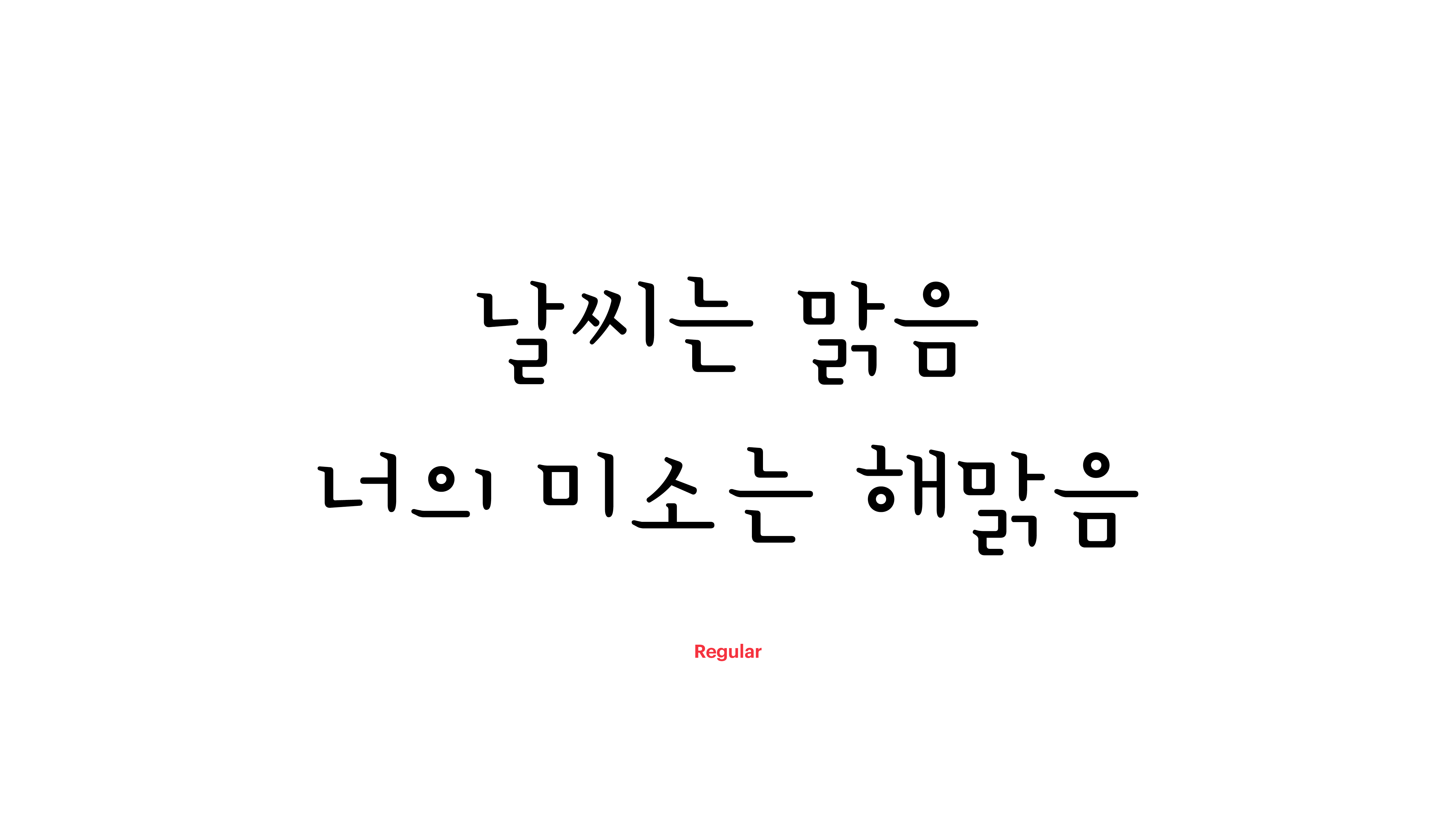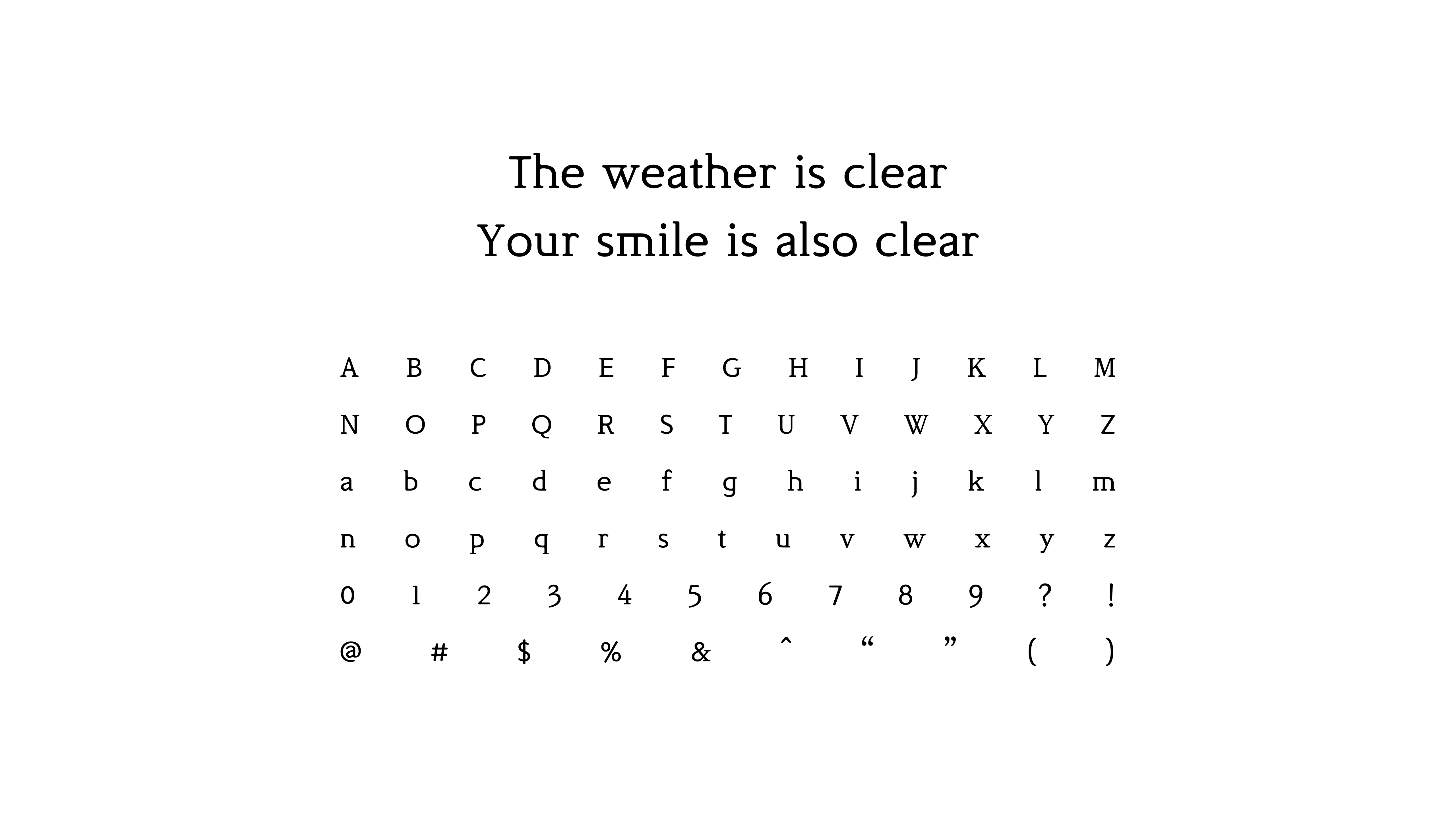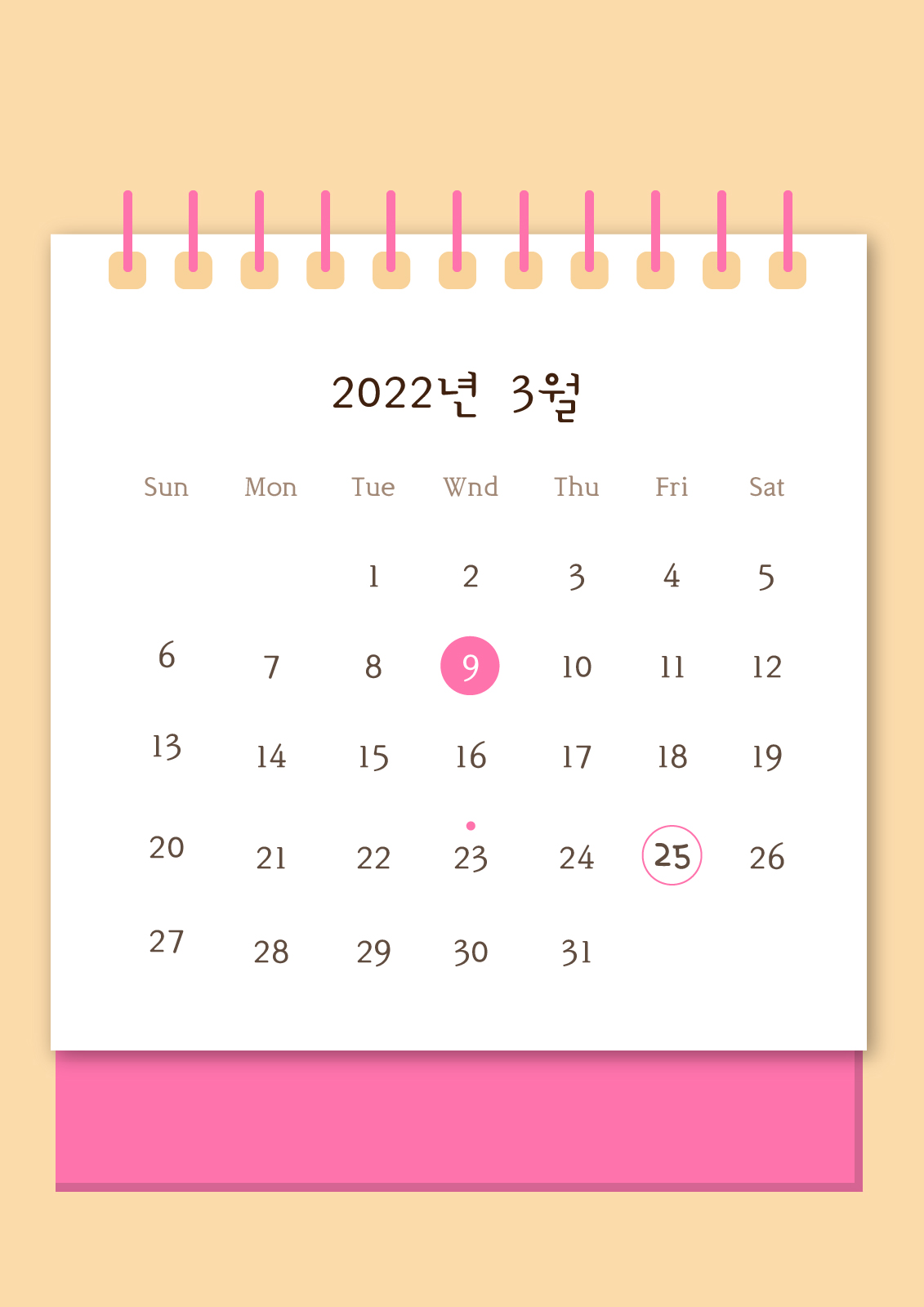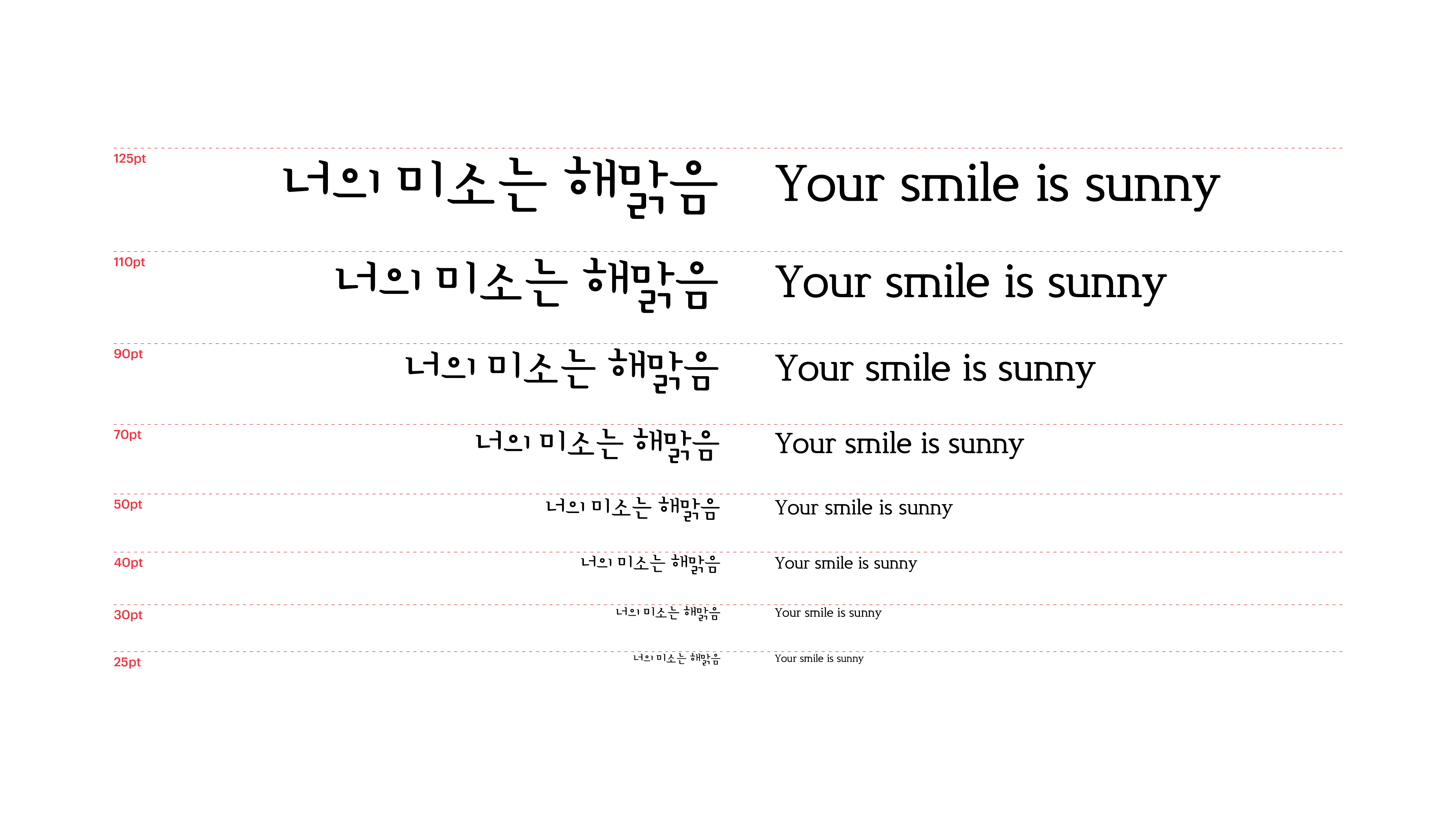
오늘은맑음
Yoon 오늘은맑음
날씨가 온통 맑음으로만 된 일기장이 있다면, 그 안에는 이런 폰트로 적힌 이야기가 빼곡할 것 같아요. 삐침이 크고 자소가 작으면서도 또박또박 필기감이 살아있는 오늘은맑음체. 오늘 여러분이 어떤 일상을 흘려보냈든, 이 앙증맞은 폰트와 함께라면 하루를 웃으면서 마무리 할 수 있을 거예요.